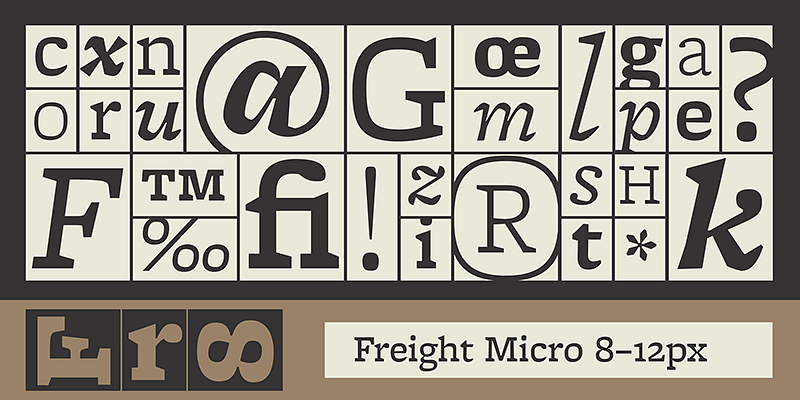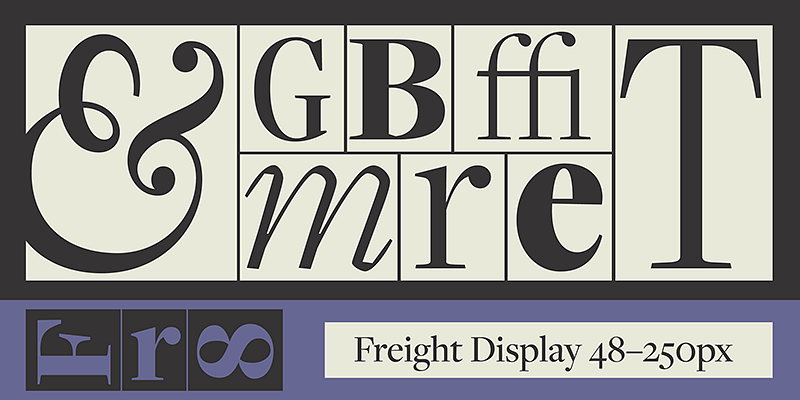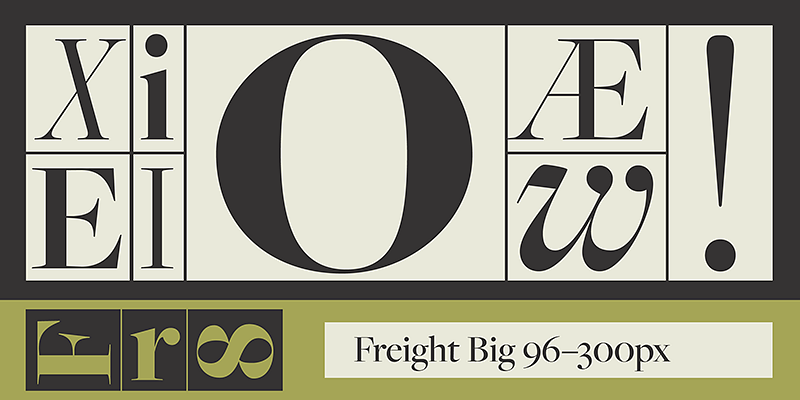
La collection Freight comprend une gamme efficace de familles de polices entrelacées, idéales pour ajouter un style unique à n’importe quel projet. Pour Joshua Darden, ce qui était au départ une famille de polices avec empattement inspirée par la chaleur et le pragmatisme typiques des typographies hollandaises du XVIIIe siècle s’étend désormais sur plusieurs graisses, chasses et tailles optiques (grand format, titrage, labeur, micro, macro et sans), toutes accompagnées également de leur version italique. Cela représente 156 fontes qui peuvent s’avérer aussi audacieuses et impertinentes que discrètes et effacées.